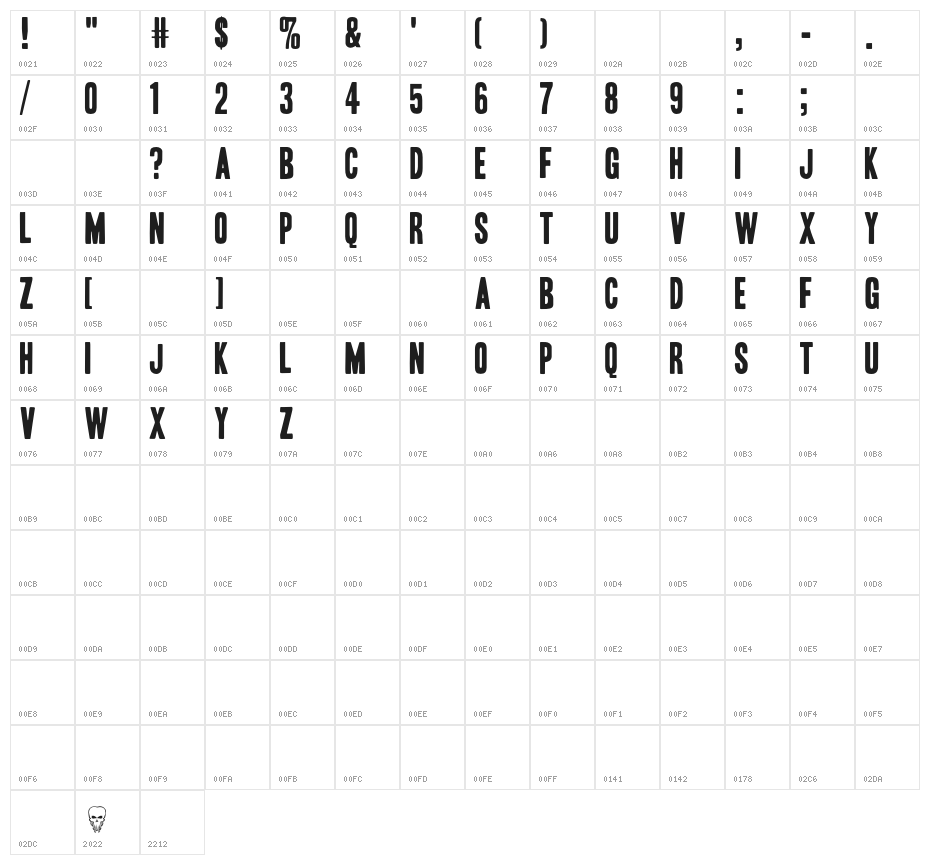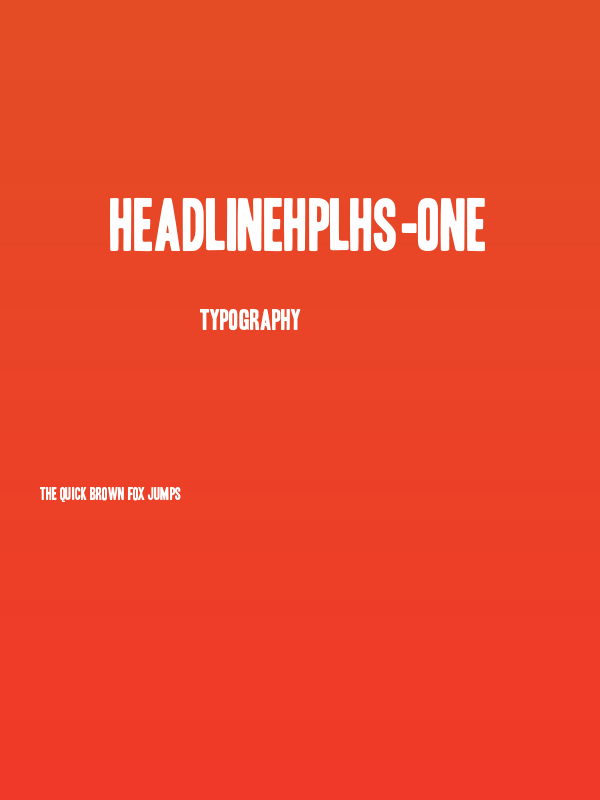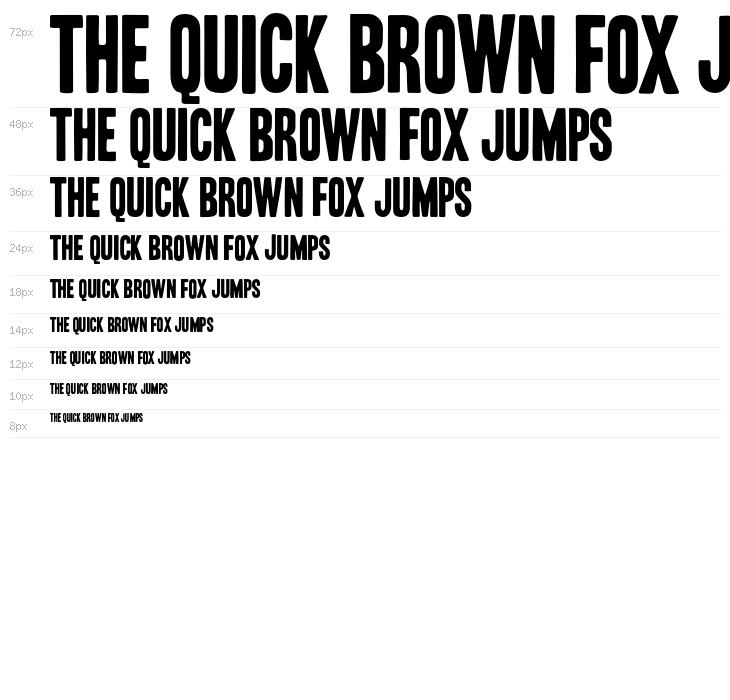
HeadlineHPLHS-One Font
| Рекомендуемые проекты | Ideal for headlines, posters, advertisements, and branding materials that require a bold and impactful typeface. |